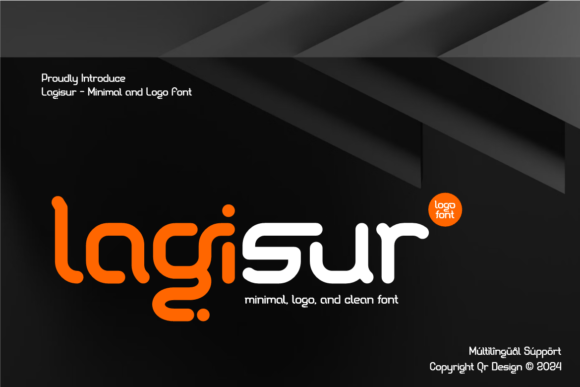
Lagisur
Jika anda sedang mencari aset berkualiti tinggi seperti Lagisur, pakej premium ini merupakan pilihan yang hebat untuk projek kreatif anda.
Dicipta dengan ketepatan, Lagisur menyediakan vektor yang bersih, tipografi yang licin dan lesen komersial untuk ketenangan fikiran.
Sama ada anda mencipta produk POD (Print on Demand), jemputan perkahwinan atau grafik media sosial, Lagisur amat bersesuaian.